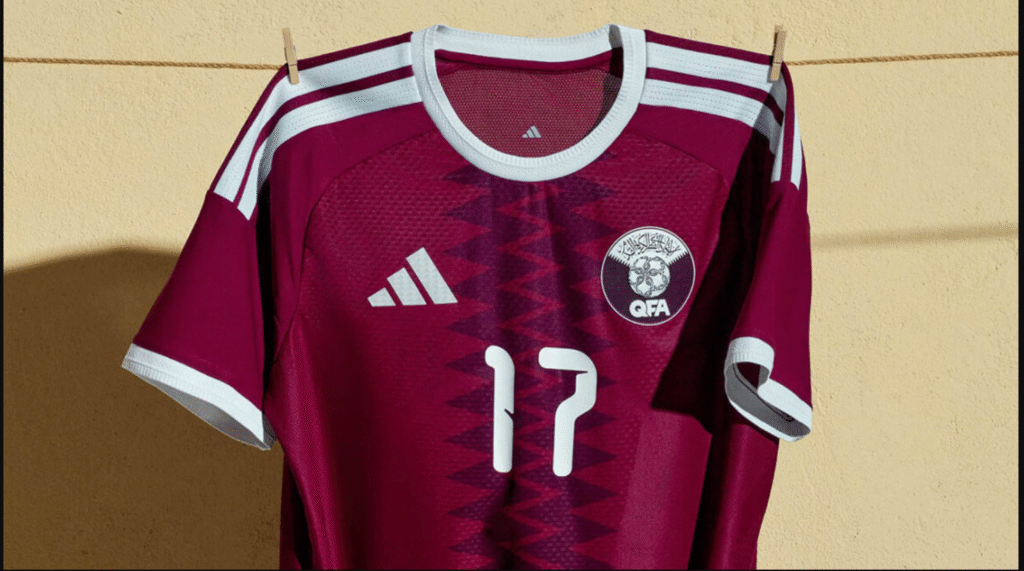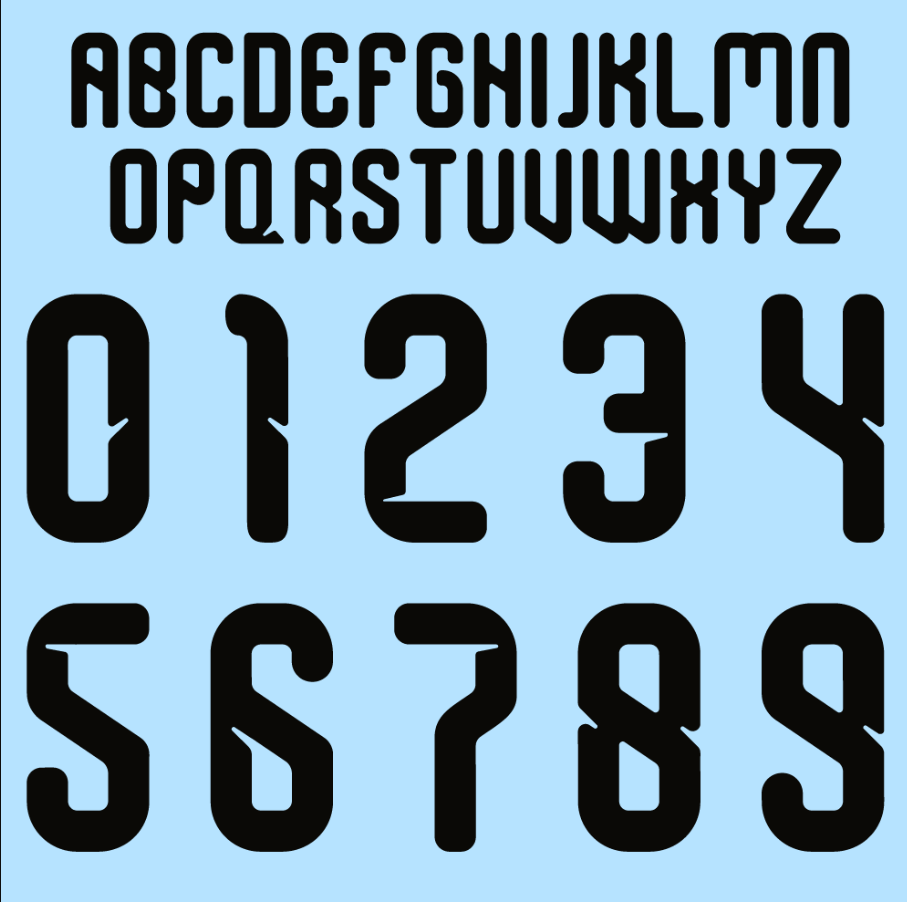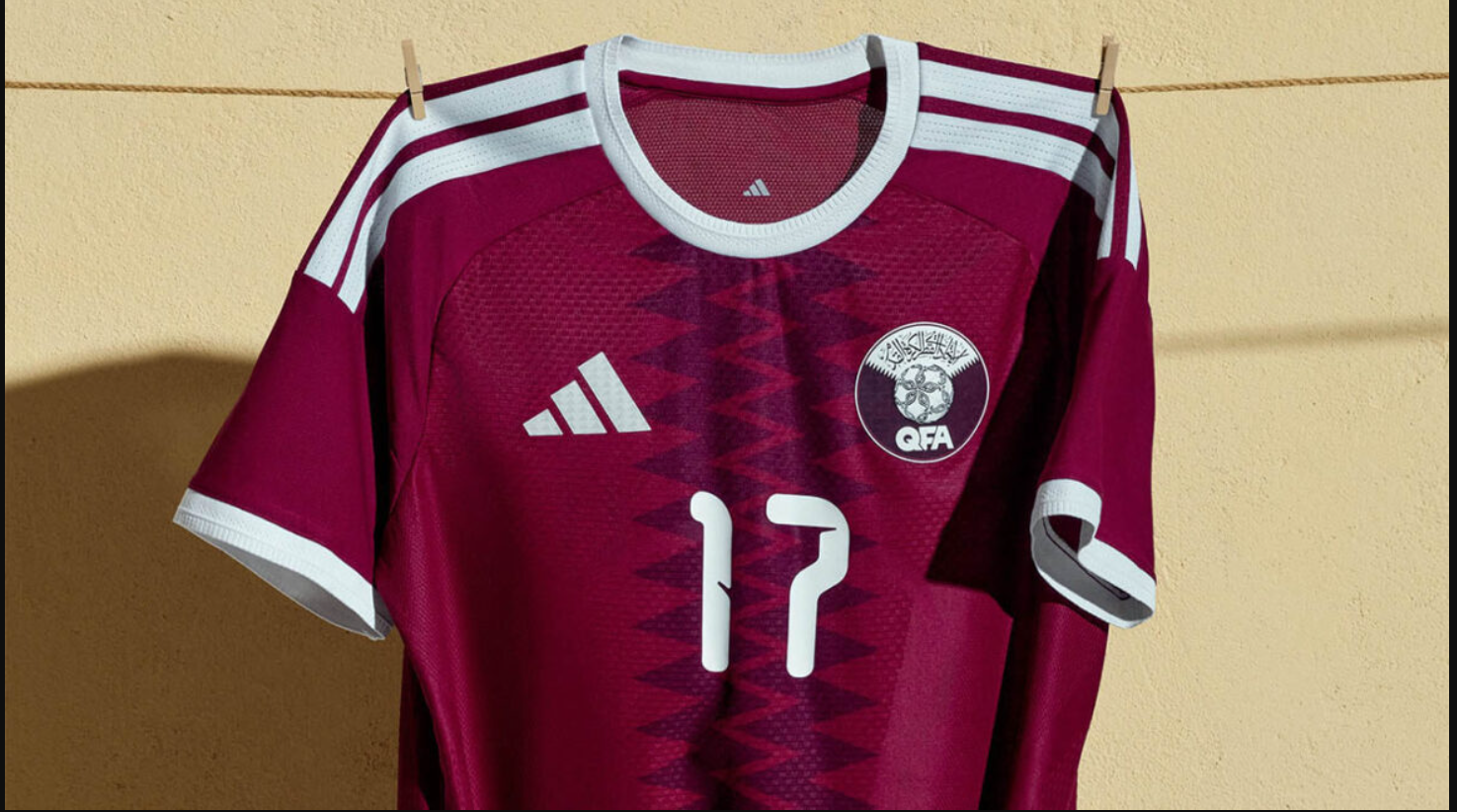
Após sediar o mundo em 2022, a Seleção do Catar (conhecida como The Maroons) inicia sua nova jornada rumo ao mundial de 2026, que ocorrerá na América do Norte. Para os designers e personalizadores que buscam manter seus projetos atualizados com os uniformes das eliminatórias e da Copa da Ásia, trazemos a tipografia oficial utilizada nos novos kits.
Se o seu objetivo é reproduzir com fidelidade as camisas produzidas pela Nike para a seleção catariana nesta nova temporada, este arquivo é indispensável.
Estilo Visual e Design
A tipografia do Catar para o ciclo 2026 mantém a identidade visual sofisticada que marca a seleção. A fonte apresenta traços que homenageiam a caligrafia árabe, com curvaturas sutis e cortes angulares modernos.
Nos uniformes titulares (Grená), a fonte geralmente é aplicada em branco ou dourado, criando um contraste elegante. Já nos uniformes reservas, ela se destaca pela legibilidade e pelo design aerodinâmico característico das fontes esportivas da Nike personalizadas para seleções nacionais. É uma fonte que transmite velocidade e tradição cultural simultaneamente.
Dica de Design: Ao utilizar esta fonte em números de dois dígitos (ex: 10, 11, 22), atente-se ao espaçamento. A fonte oficial costuma ser levemente condensada para caber harmoniosamente nas costas da camisa.